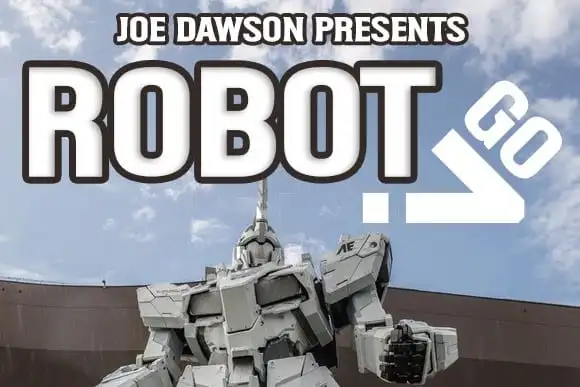
Robot Go Display Font é uma tipografia industrial sci-fi que oferece duas estilos únicos. Esta tipografia de exibição é completa com letras maiúsculas, números e sinais de pontuação básicos. Adicione essa fonte a seus projetos criativos para ver como ela os faz se destacar! É perfeita para aplicação em posters, mídia social, headlines, grandes impressões – e qualquer lugar onde você deseja chamar atenção. Composto por letras maiúsculas, números e sinais de pontuação básicos, este tipo de exibição do Robot Go é uma escolha ideal se você está buscando destacar seus projetos. Seu destaque em posters, redes sociais, headlines e grandes formatos não só aumentará a visibilidade dos seus trabalhos, mas também manterá um tom inovador e futurista que combina perfeitamente com o tema industrial sci-fi.